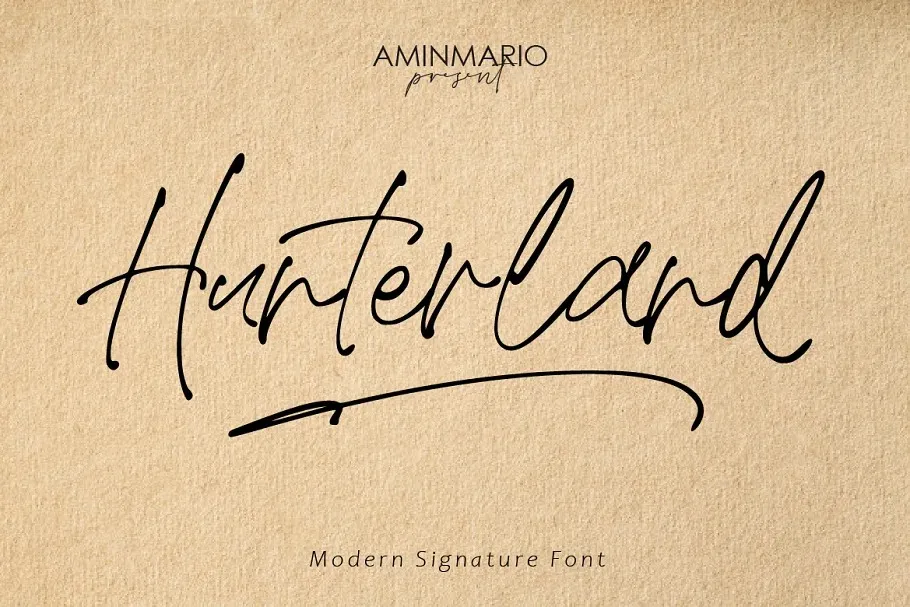
Hunterland Font
A Hunterland Font é uma fonte script criada com habilidades artísticas humanizadas para combinar elementos de escrita moderna com detalhes manuais desenhados à mão. Compatível perfeitamente com os projetos que exigem um toque de escrita humana, esta font foi concebida e compartilhada por AMINMARIO. O objetivo da Hunterland é manter uma proximidade incrivelmente próxima do estilo de escrita manual, incluindo alternativas para letras minúsculas, ligação de caracteres e linhas sublinhadas. É perfeitamente adequada para qualquer projeto que precise de um toque autêntico de escrita à mão. A Hunterland é uma escolha ideal para designers em busca de adicionar um elemento pessoal ao seu design gráfico.